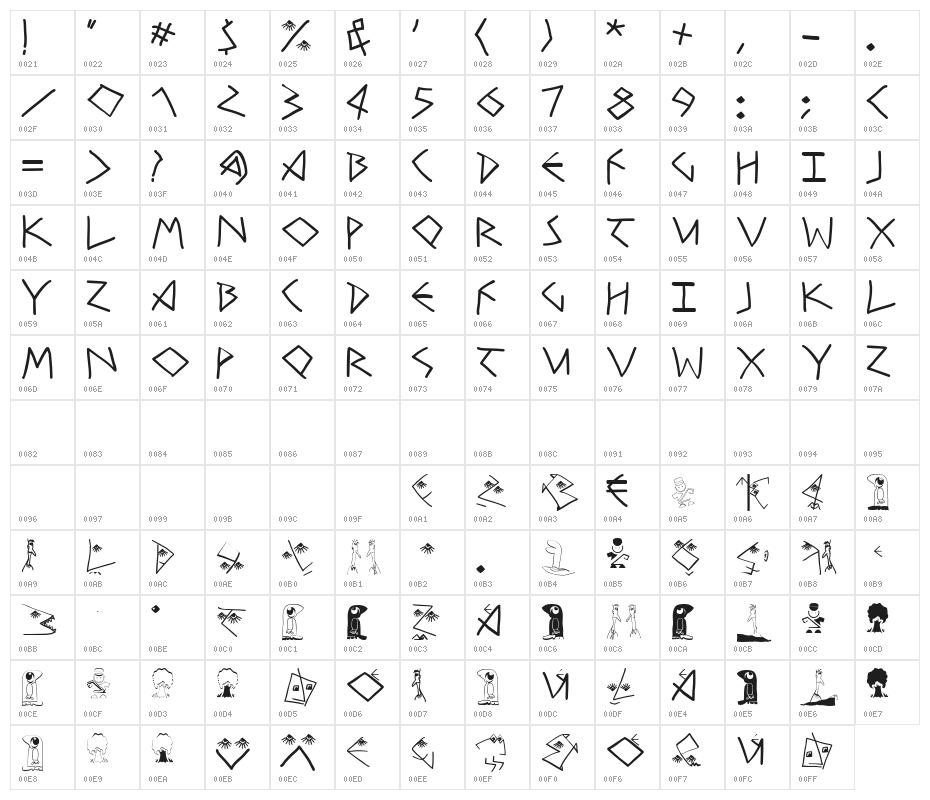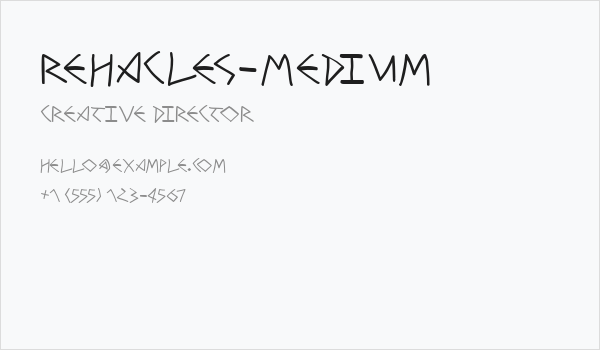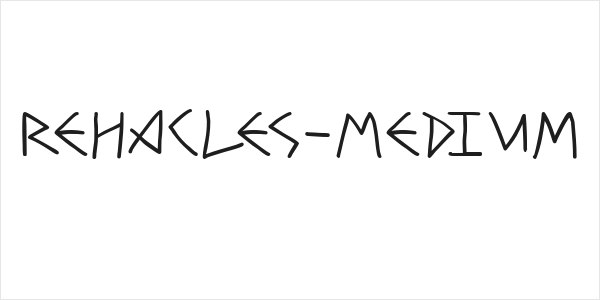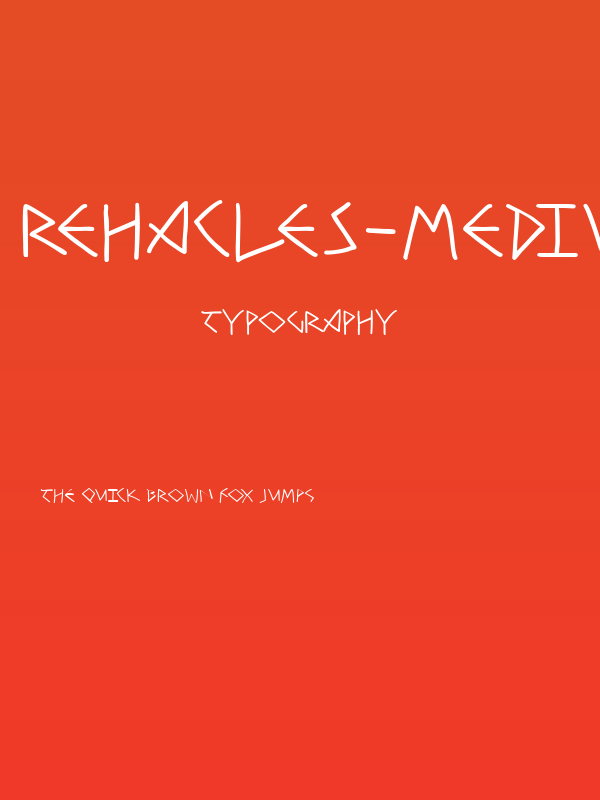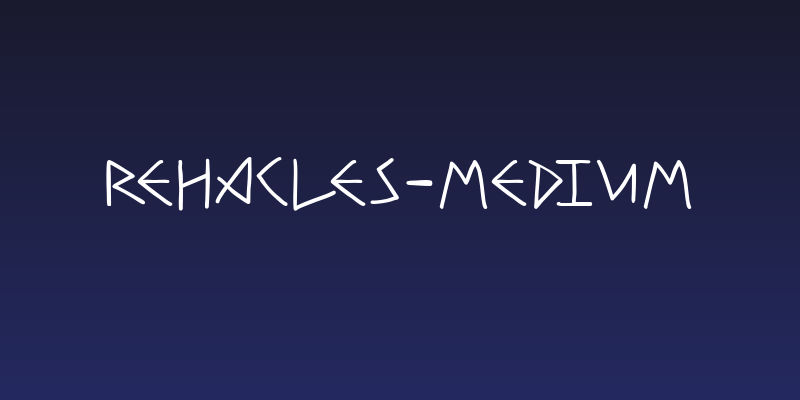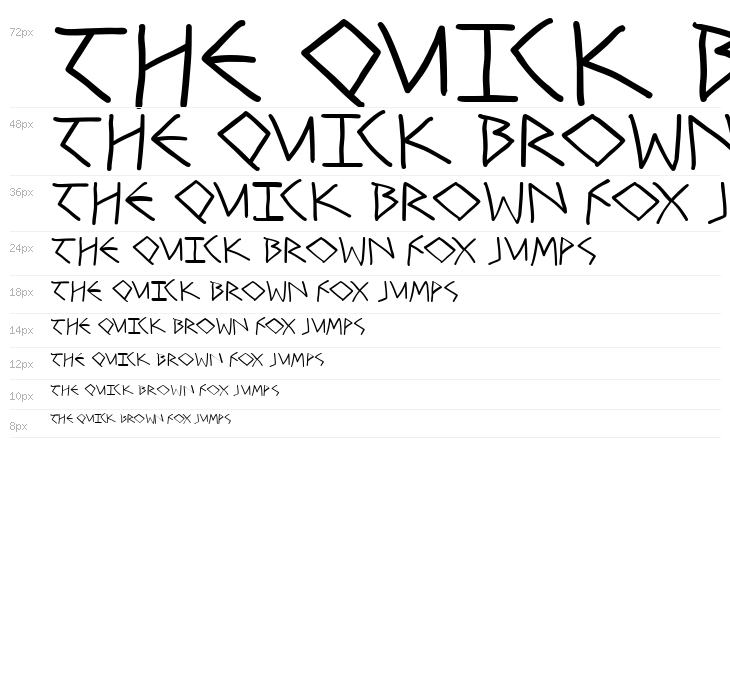
Rehacles-Medium Font
✎ Thick
| Vorgeschlagene Projekte | Ideal for fantasy-themed designs, game titles, posters, and branding that requires a mystical or ancient aesthetic. |